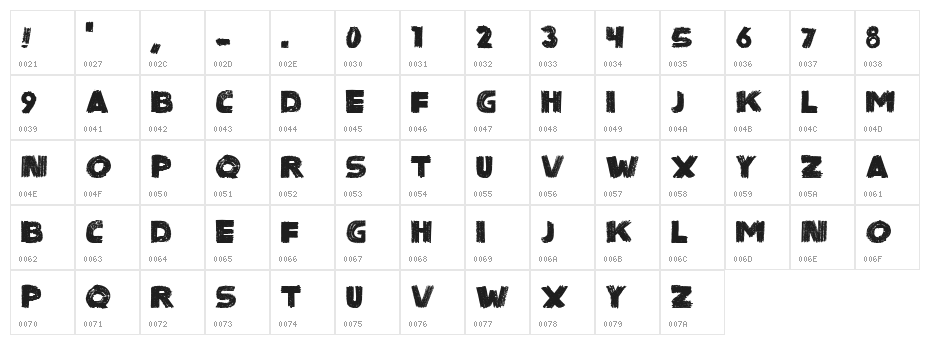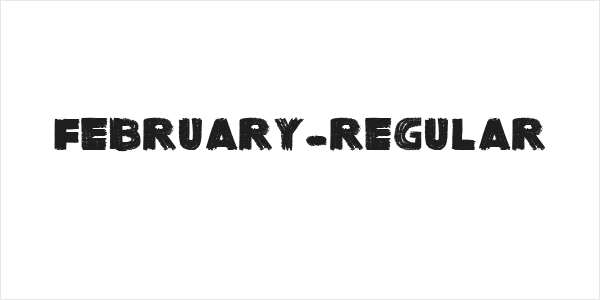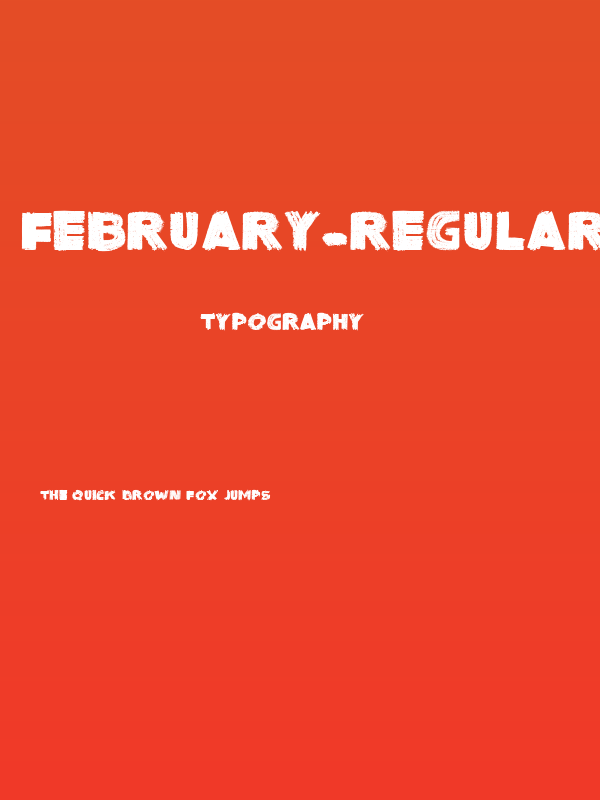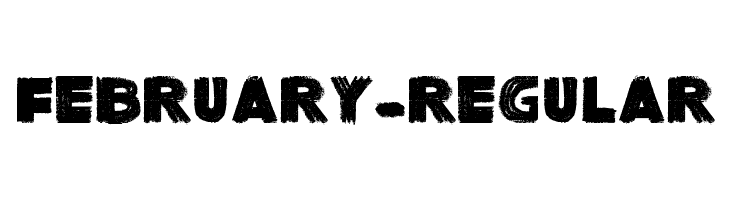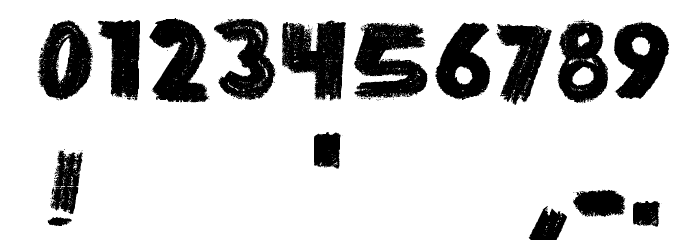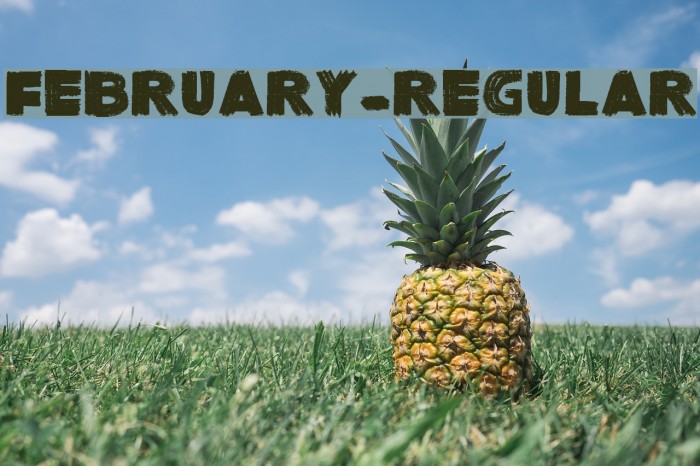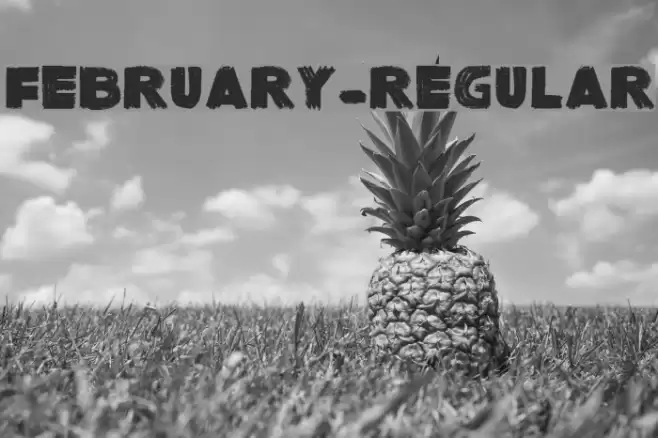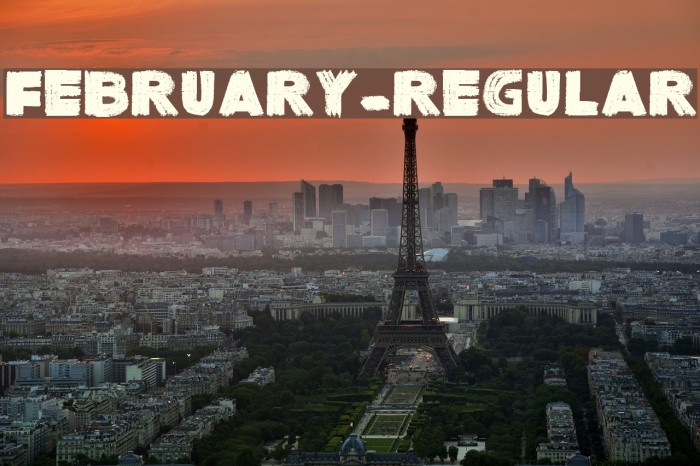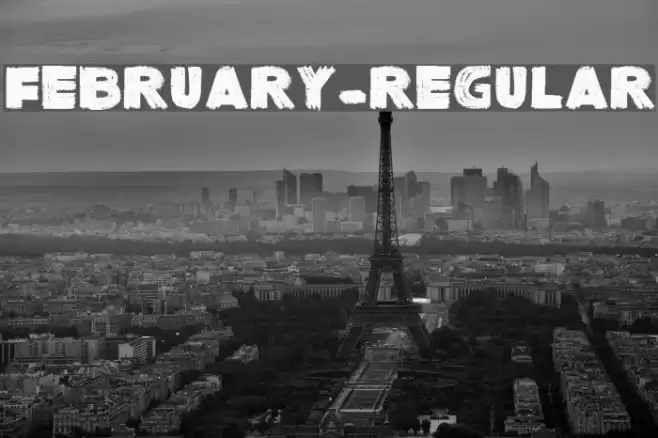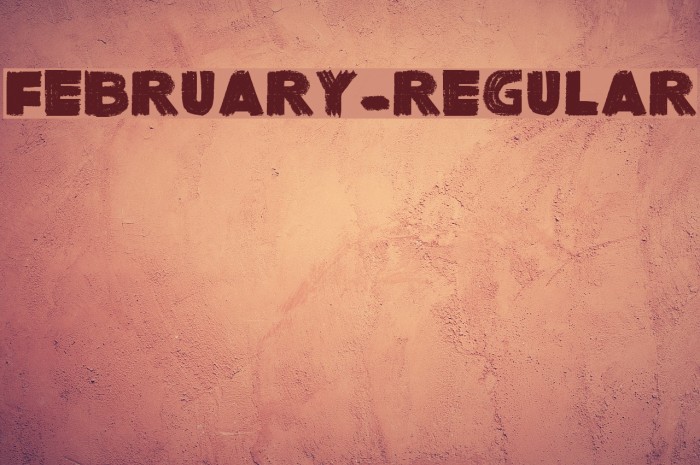
February-Regular Font
| Stil general | Artistic, Bold, Textured |
| Caz de utilizare | Headlines, Posters, Branding |
| Proiecte propuse | Ideal for posters, branding, headlines, and any creative projects that require a strong, artistic visual impact. |